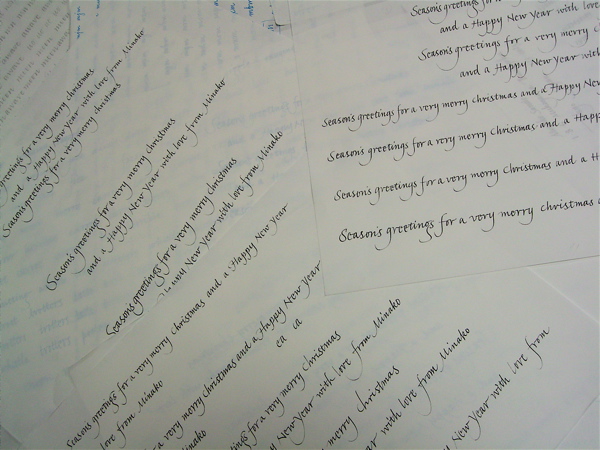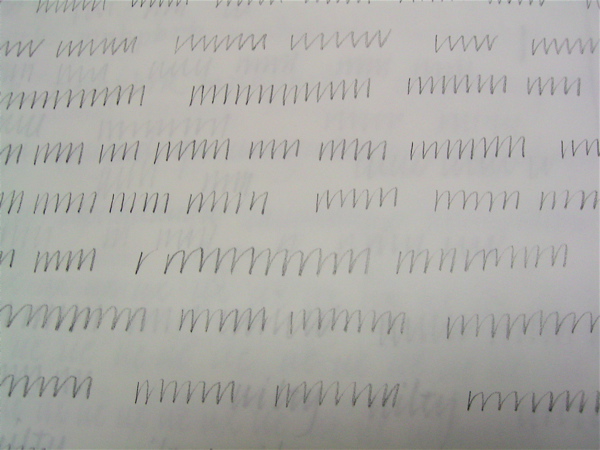
ハンドライティング
ハンドライティングのクラスです。
私たちにとっては普段アルファベットで文章を書くことが少ないので、ハンドライティングとカリグラフィーの用途の違いというのは余りないかもしれませんが、本来は道具は同じペンでも書き方がずいぶん異なる事がわかりました。
筆記体なのでつなげて書きますから、文字の組み合わせによっていろいろと書き方が違うわけです。入り方と出方、つなげ方をひらすら書く、書く、書く。書いては休み、そしてまた書く。
普通のカリグラフィーの練習だと、ペンを出して、インクを開けて、とおっくうになってしまう事もありますが、このハンドライティングでは、鉛筆と紙だけでよいのですから、テレビを見ながらでも、練習出来るのです。
とてももったいないですよね。
うちの娘はアメリカの小学校に通っていた時、お姉さんたちが書いているcursiveにものすごく憧れていて、「早くクーシフ(そう聞こえました)を書きた〜い」と言って見よう見まねで書いていました。めちゃくちゃっでしたが!
ふ〜む、普通のカリグラフィーも難しいけれど、ハンドライティングを美しく書くはやはり一生懸命練習しなければならないのだなぁ。
私は以前、別の人のハンドライティングを使うWSを受けたことがあります。このハンドライティングというやつは、英語が苦手な私にとっては難しい作業でした。続けてリズムよくどんどん書かないといけないのに、いちいち単語を確認、スペルを確認・・・。リズムのない文字たちがずら〜っと並んだ覚えがあります。mojitor-sさんのおっしゃるとおりTVを見ながら練習できますね。とは言ってもめんどくさがりぃなので、なかなか・・・。実行あるのみなのは分かっているのですが・・・。
そうそう、わかります!
スペルを考えながら書くと手が止まり、考えないで書くと綴りは怪しくなってしまいます。
今回のWSで受講した練習の中でいいな、と思ったのは、a〜zをすべてnの間に入れて書いていくやり方です。nan nbn ncn ndn nen nfn・・・・・というように。もしかしたらuau ubu ucuも効果的かもしれませんね。nとuでは同じ文字からでもつなげ方が変る場合があった様に思いました。
これなら単語としてではないので、失敗することもないしね(^^)
それでも頭の中は、えーと、えーとになってしまいますが・・・・。
お試し下さ〜い。